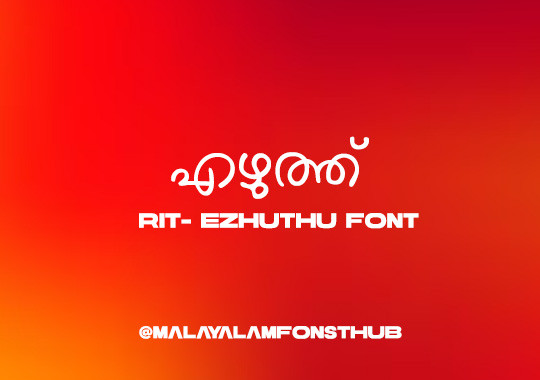
Ezhuthu | Traditional Handwriting Style Malayalam Font
മലയാളം കാലിഗ്രാഫി ഇതിഹാസം നാരായണ ഭട്ടതിരിയുടെ (Narayana Bhattathiri) വിരൽത്തുമ്പിൽ നിന്നും ഉടലെടുത്ത മനോഹരമായ അക്ഷരരൂപങ്ങളാണ് Ezhuthu എന്ന ഫോണ്ടിലൂടെ ഡിജിറ്റൽ ലോകത്തേക്ക് എത്തിയിരിക്കുന്നത്. രചന ഇൻസ്റ്റിറ്റ്യൂട്ട് ഓഫ് ടൈപ്പോഗ്രാഫി (RIT) വികസിപ്പിച്ചെടുത്ത ഈ ഫോണ്ട്, മലയാളത്തിന്റെ പഴയ ലിപി (Traditional Script) ശൈലിയിലാണ് രൂപകൽപ്പന ചെയ്തിരിക്കുന്നത്. പേന കൊണ്ട് പേപ്പറിൽ എഴുതുന്ന കൈയക്ഷരത്തിന്റെ അതേ സ്വാഭാവികത ഈ ഫോണ്ട് ഡിസൈനുകൾക്ക് നൽകുന്നു.
പ്രത്യേകതകൾ:
Authentic Calligraphy: പ്രശസ്ത കാലിഗ്രാഫർ നാരായണ ഭട്ടതിരിയുടെ തനതായ ശൈലിയിലുള്ള അക്ഷരരൂപങ്ങൾ.
Traditional Script: മലയാളത്തിന്റെ പൗരാണികമായ ലിപി വിന്യാസത്തെ (Old Script) പിന്തുണയ്ക്കുന്ന രീതിയിലുള്ള നിർമ്മാണം.
Expert Craftsmanship: ഹുസൈൻ കെ.എച്ച് (Typography), രാജീഷ് കെ.വി (Font Engineering) എന്നിവരുടെ സാങ്കേതിക മികവിൽ പൂർത്തിയാക്കിയ ഫോണ്ട്.
Rachana Legacy: ആർ. ചിത്രകുമാർ തുടക്കം കുറിച്ച 'രചന' പ്രസ്ഥാനത്തിന്റെ ഭാഗമായി, പരമ്പരാഗത അക്ഷരക്കൂട്ടുകളെ നിലനിർത്തിക്കൊണ്ടാണ് ഇത് പുറത്തിറക്കിയിരിക്കുന്നത്.
Personal Letters ഡിജിറ്റലായി തയ്യാറാക്കാനും, കവിതകൾക്കും, പുസ്തകങ്ങളുടെ കവർ ഡിസൈനുകൾക്കും, കൂടാതെ മലയാളിത്തമുള്ള സോഷ്യൽ മീഡിയ പോസ്റ്ററുകൾക്കും Ezhuthu ഫോണ്ട് അനുയോജ്യമാണ്.